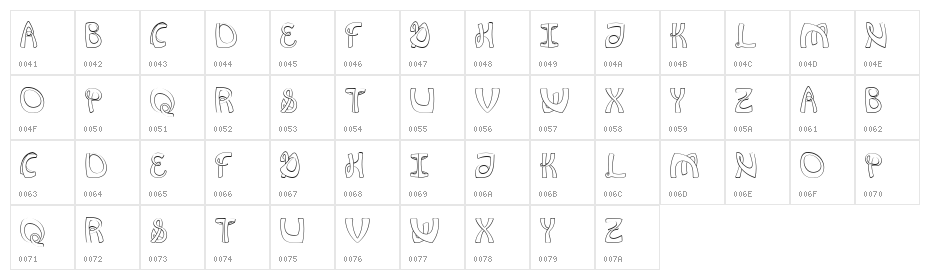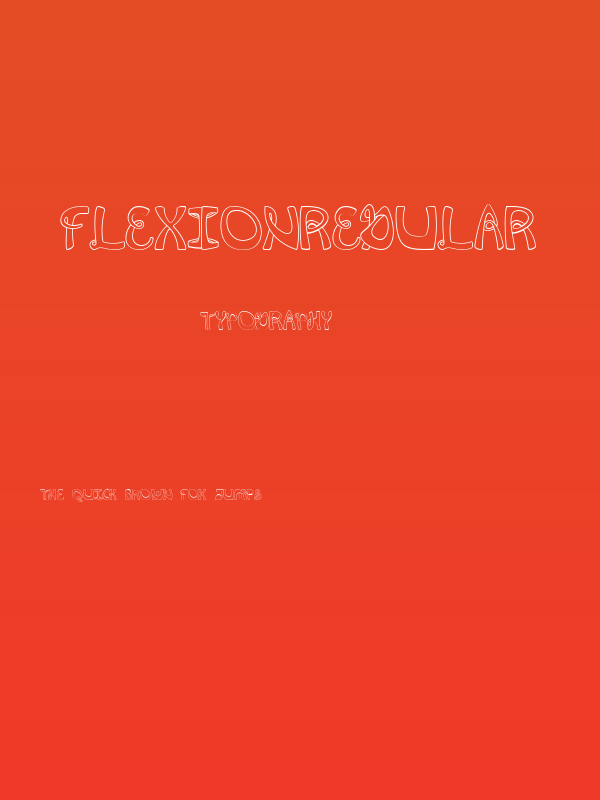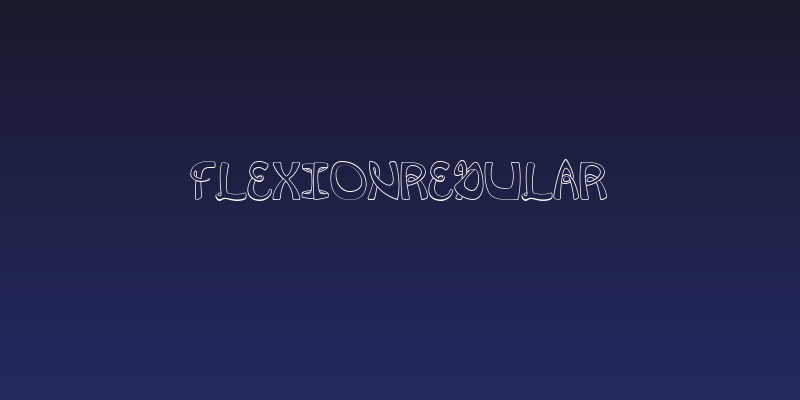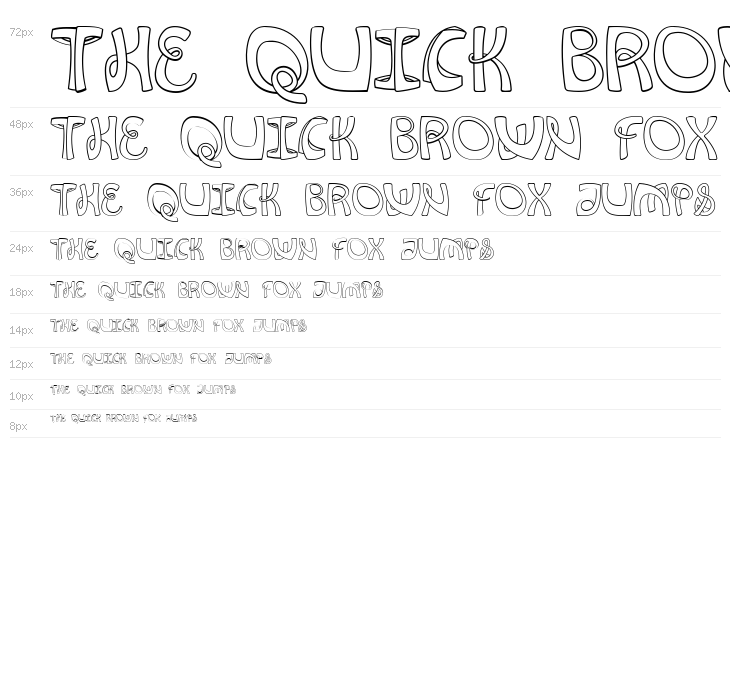
FlexionRegular Font
| Proyectos propuestos | Ideal for creative projects such as children's books, playful branding, artistic posters, and unique invitations. |
FlexionRegular